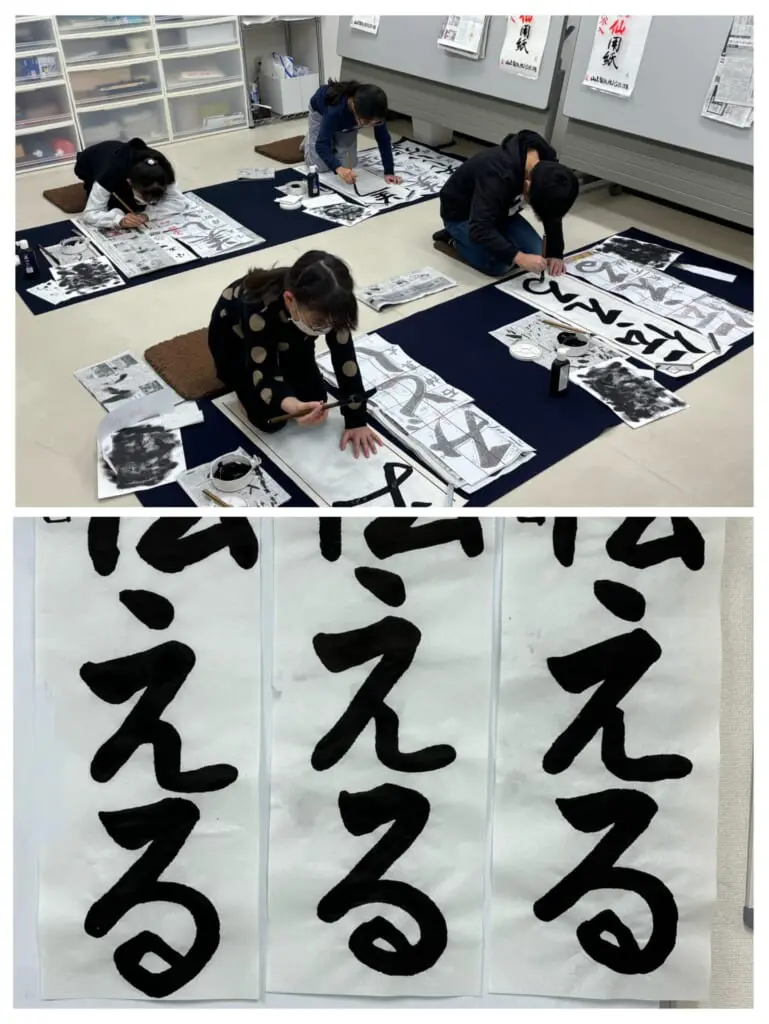
みなさん、「苦手だなぁ」と思う字ってありませんか?大人でも「この字だけはきれいに書けない」というものがあったりしますよね。実は、子どもたちにも同じようなことがあるんです。でも、苦手な字と向き合って練習してみると、驚くほどきれいに書けるようになることがあります。今日は、そんな嬉しい瞬間をご紹介します!
今日、ある生徒さんが書き初めの練習で「伝える」という課題文字に挑戦していました。中でも最後の「る」がなかなか形よく書けず、悩んでいました。練習した作品を並べて、「なんか変!」と話す姿が印象的でした。
そこで、「どうしたら形良くなると思う?お手本と見比べてみて」と声をかけると、生徒さんは手本をじっくり観察し、「下部の楕円の空きが小さいこと」と「楕円の中心が右にずれていること」を発見!そのポイントを意識しながら丁寧に書き直してみました。すると、とても形よい「る」が書けたんです!
その瞬間、生徒さんの表情は、何とも言えない嬉しそうなニコニコの笑顔。「できた!」という声に、周りの私たちも自然と笑顔になりました。その後の練習でも、同じように上手に書けていました。
短い時間でここまで変化するのは、本当にすごいことです。その生徒さんが「苦手な字を書けるようになりたい」という気持ちを持ち、自分で考えながら取り組んだ結果だと思います。子どもたちが苦手なことに向き合い、成功体験を重ねていく姿には、毎回驚かされます。
書道の魅力は、美しい文字が書けるようになるだけでなく、「できなかったことができるようになる」達成感を味わえるところにあります。もじもじでは、子どもたち一人ひとりのペースや性格に合わせて、苦手な字にも楽しく挑戦できる環境を大切にしています。